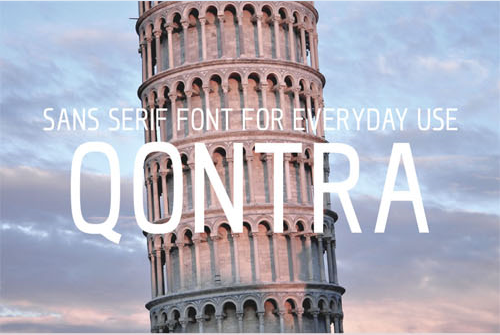
Qontra Sans Serif Font – Download Grátis
A Qontra Sans Serif é uma excelente opção para projetistas que procuram um tipo ganchudo sem serif, ideal para trabalhos informais, capas e design editorial, como livros ou revistas. Com um contraste baixo que proporciona uma leitura confortável, ela se destaca por sua elegância sob medida, perfeitamente adaptada a qualquer texto. Essencialmente projetado para aplicações de tipografia informativas e visuais, este tipo é ideal para assegurar um design fluido e moderno em variados formatos de mídia. É especialmente adequado para a criação de fontes de leitura rápida e textos gráficos promocionais ou publicitários, garantindo sempre uma aparência clara e profissional. Seja você um designer de revistas, um especialista em design editorial ou até mesmo um criador de materiais de marketing, a Qontra Sans Serif é uma escolha sólida para atender às suas necessidades específicas.